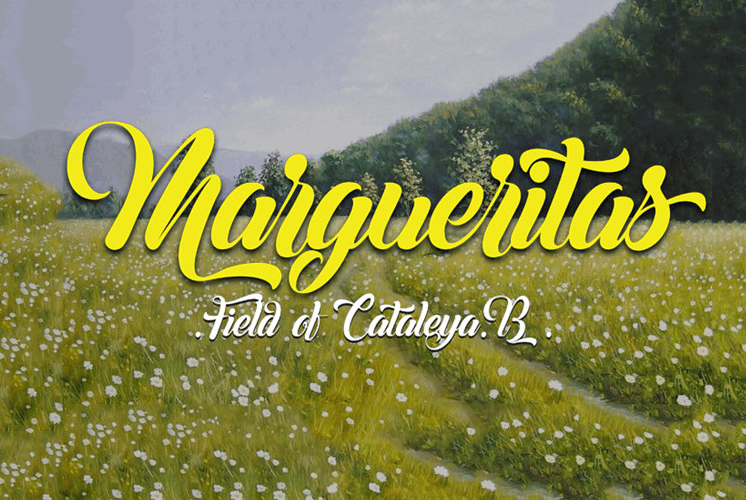
Margueritas Font
Aqui está uma descrição para a página de download da font ‘Margueritas Font’, focando nas características desejadas: A nossa fonte ‘Margueritas’ é perfeita para artistas e designers que desejam trazer um toque único à sua arte, seja ela calligrafia ou qualquer outro formato. Esta elegante família de fontes foi criada pelo designer Cat Butcher, com uma linguagem simples e intuitiva que facilita a sua integração nas suas criações. A ‘Margueritas Font’ é ideal para projetos personais, incluindo artesanato, design pessoal ou qualquer outro uso doméstico. No entanto, para utilizações comerciais, seja em elementos de marketing, gráficos publicitários ou outros formatos que possam ser vendidos, o designer Cat Butcher exige um pré-aviso antes da utilização. Por razões éticas e respeitosas à sua arte, a fonte ‘Margueritas’ não pode ser usada em conteúdos sexuais. É importante lembrar estas regras para garantir que a nossa fonte seja usada de maneira responsável e respeitosa. Se você está interessado na adquirir esta exclusiva fonte ou deseja obter mais informações, é fácil entrar em contato com o designer por meio do email: .